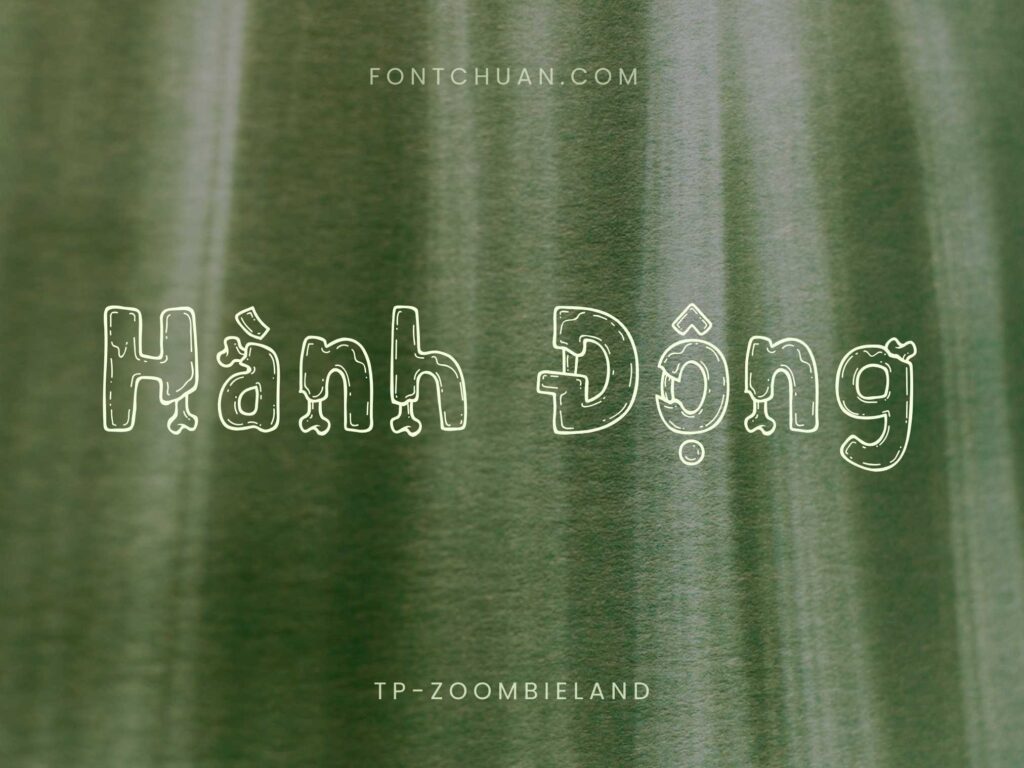
Font TP Zombieland Việt Hóa
Zoombieland là một font chữ phong cách hoạt hình, được thiết kế bởi Mehibi. Với vẻ ngoài vui nhộn, năng động và tràn đầy sức sống, đây là một Font chữ quảng cáo được ưa chuộng trong các thiết kế hướng đến sự tươi mới và sáng tạo. Font đã được Việt hóa để hỗ trợ tiếng Việt bởi Tuỳn Pucca, giúp người dùng Việt Nam dễ dàng áp dụng trong các dự án của mình. Font này được sưu tầm và chia sẻ bởi thành viên của Font Chuẩn, đáp ứng nhu cầu sử dụng đa dạng trong cộng đồng thiết kế.
Đặc điểm thiết kế của Zoombieland bao gồm các nét chữ đậm và ngộ nghĩnh, tạo cảm giác thân thiện và vui tươi. Font này phù hợp cho các ứng dụng như thiết kế tiêu đề, logo, poster và các dự án sáng tạo khác. Các ngành nghề phù hợp bao gồm quảng cáo, nghệ thuật và thiết kế đồ họa.